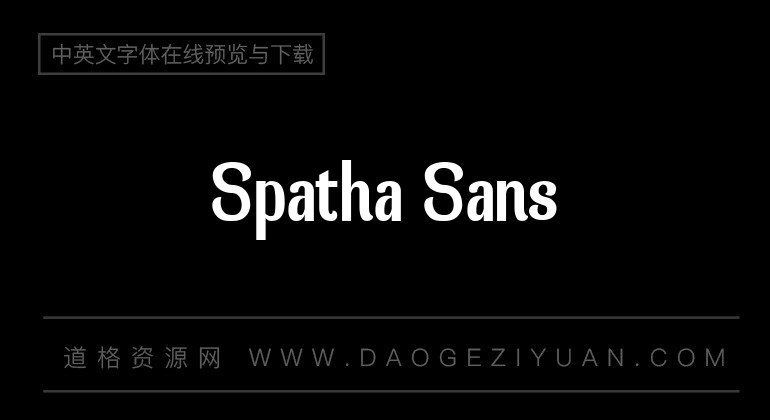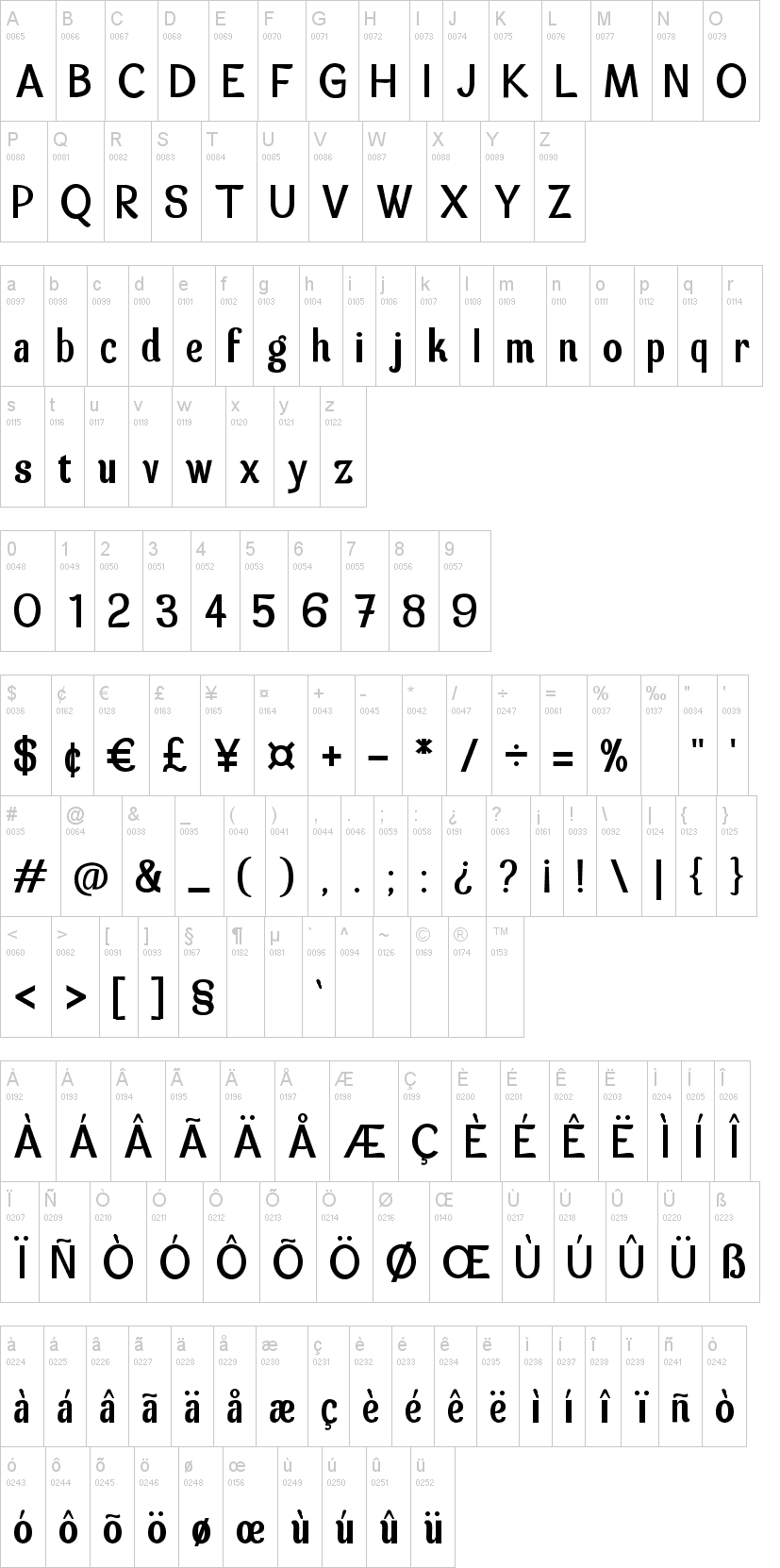
Spatha Sans
Spatha Sans是一种无衬线(sans-serif)字体,由设计师Steve Matteson于2019年创建。该字体旨在成为现代、精简和高可读性的字体,适用于电脑、手机等各种数字设备上显示。 Spatha Sans有7个字重,包括Thin、ExtraLight、Light、Regular、Medium、Bold和Black,支持拉丁字母、西里尔字母和希腊字母。其设计灵感来自于LCD屏幕上的字体,因此具有清晰易读、简化线条的特点。此外,Spatha Sans还有一些特殊的字形设计,如小写字母a、g、y的尾巴向上翘起,以及字母k、x的斜线上有一些微妙的弯曲。 总的来说,Spatha Sans是一种现代化的无衬线字体,适用于数字设备上的各种应用场景。
Spatha Sans是一款非常不错的手写艺术字体,具有很好的视觉感,适合于文化类的宣传设计、商业类品牌的广告和产品包装设计以及个性化文字排版等较多场景。
Spatha Sans字符映射图